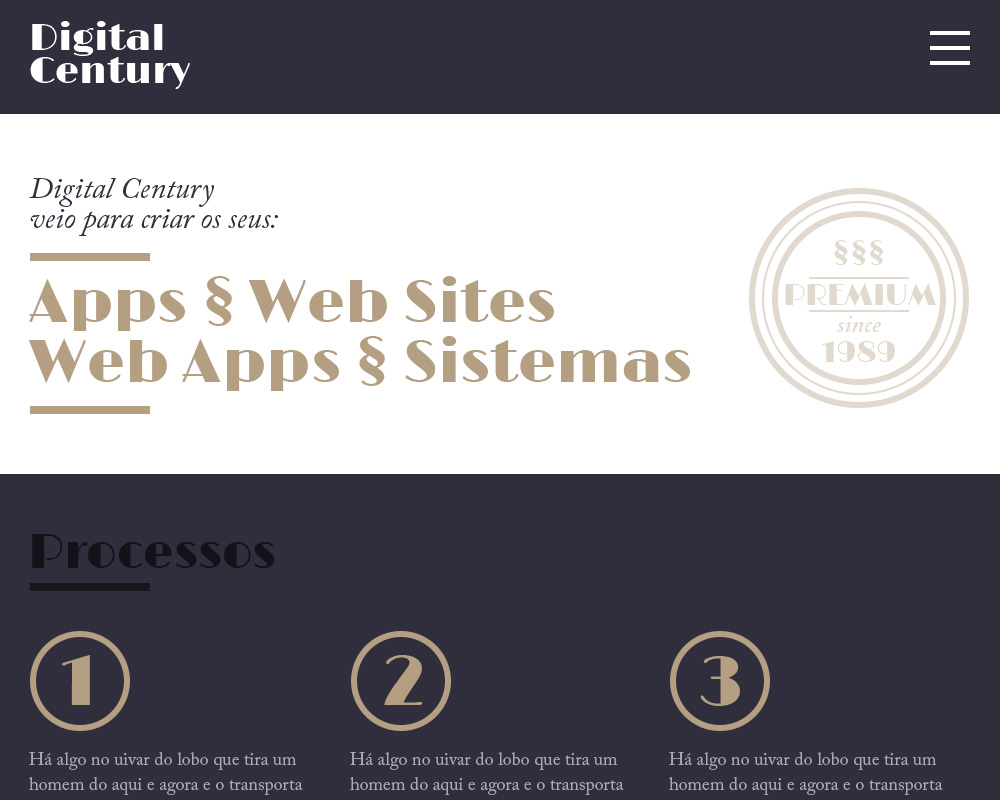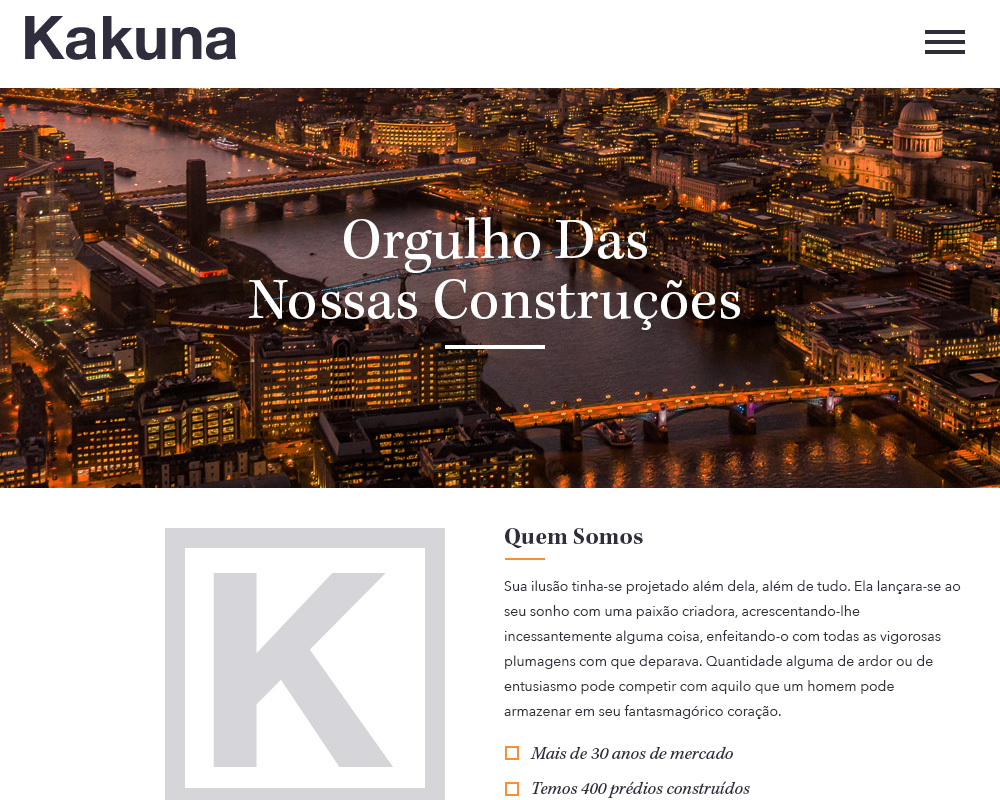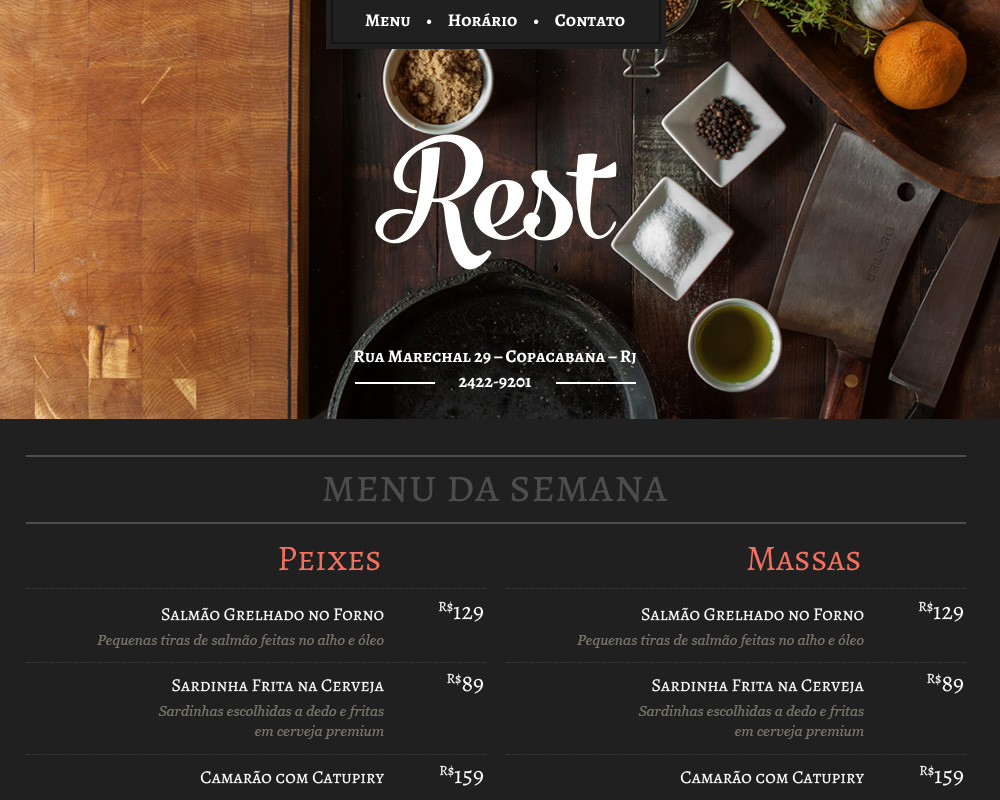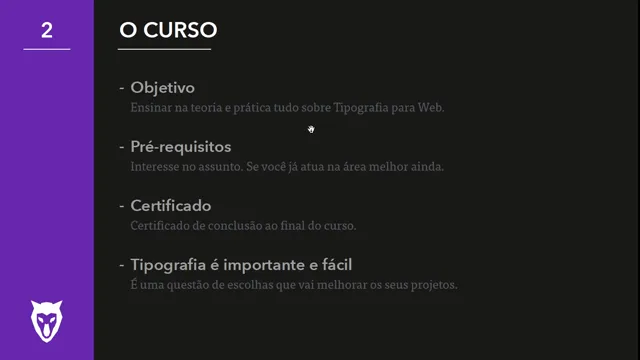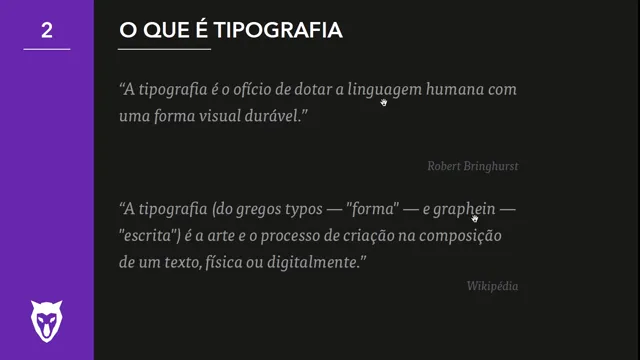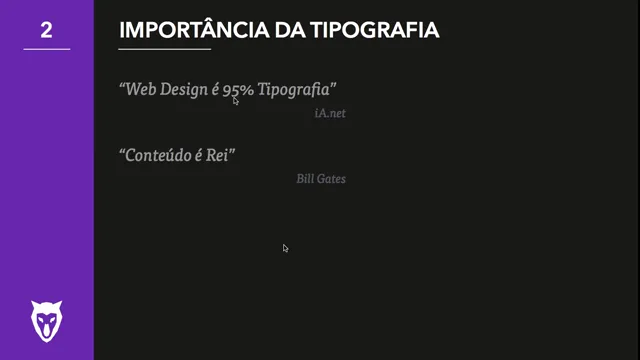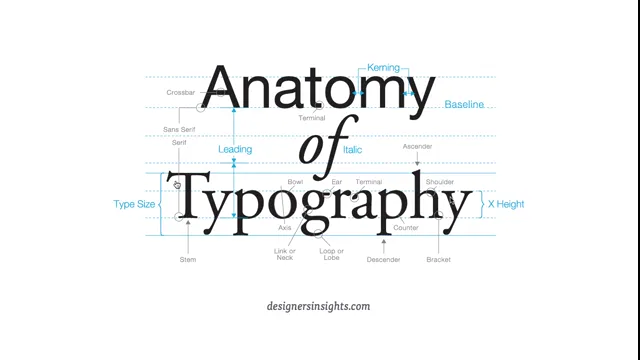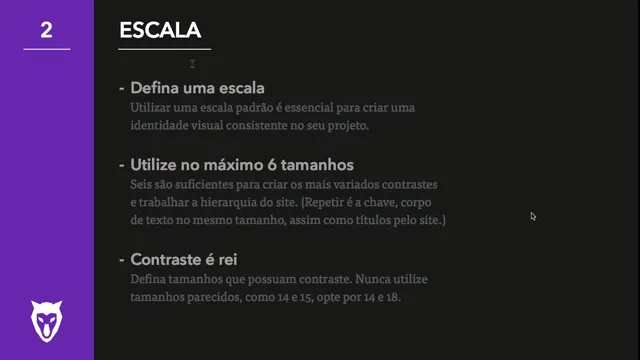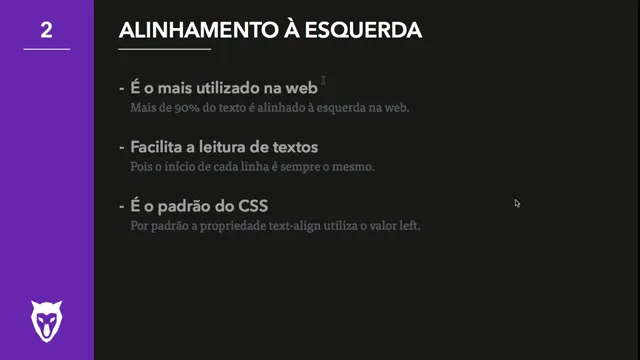
Tipografia Avançada
Este é o curso mais avançado de tipografia para Web que existe no Brasil. Qualquer pessoa interessada no assunto pode fazer o curso, pois todos os assuntos serão abordados do zero. Vamos aprender as classificações tipográficas - Serifadas, Sem Serifas, Script e Mais - e como utilizá-las na web. Também veremos como utilizar as principais variáveis tipográficas que são a Altura de Linha, Largura do Texto, Escala do Tipo, Cores e mais.
Tipografia é um dos assuntos mais importantes para qualquer Web Designer, já que 95% de toda a web é composta apenas por textos. Manipular textos é fácil o difícil é fazer da forma correta. Com este curso você irá melhorar em 80% qualquer projeto que você já tenha feito ou ainda irá fazer. E tudo isso de forma bem fácil, sem necessidade de nenhum talento, basta interesse no assunto.
- Tipografia
- Escala
- Largura do Texto
- Alinhamento
- Serifadas
- Sem Serifas
- Serifas Grossas
- Script
- OpenType
- Separadores
- Grid
- Fontes Externas
- UI Design
- UX Design
Projeto do Curso
Vamos começar o curso falando sobre a teoria e mostrando muitos exemplos na prática, de como a teoria é aplicada na Web. O que não pode faltar é a prática e por isso vamos partir para o Photoshop para criarmos layouts baseados totalmente em escolhas tipográficas.
- 1 Introdução
- 2 Variáveis Tipográficas
- 3 Classificações Tipográficas
- 4 Tipografia Para Web na Prática
- 5 Tipografia e CSS
- 6 Mais Tipografia
- 7 Considerações Finais